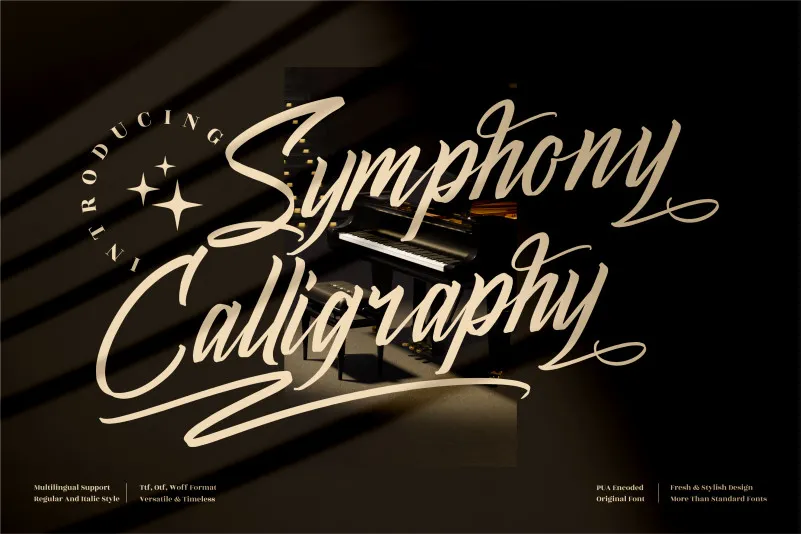
A Symphony Calligraphy Font é uma elegante escolha para projetos que exigem um toque refinado e sofisticado. Criada pelo designer perspectype, ela traz a frescor de um moderno script font sem perder a delicadeza de uma chamada à arte. Esta fonte premium está especialmente indicada para diversas aplicações onde o toque de luxo é essencial, como logotipos, projetos de marca, designs para móveis, embalagens de produtos, e até mesmo em etiquetas e sobras da fotografia. Com uma mistura única de modernidade e elegância que a Symphony Calligraphy Font oferece, ela se adapta perfeitamente a um amplo espectro de trabalhos. Seja você um designer gráfico, criador de conteúdo digital ou mesmo um estilista de moda, essa fonte será uma excelente adição à sua coleção, dando um toque especial e autêntico aos seus projetos mais sofisticados.